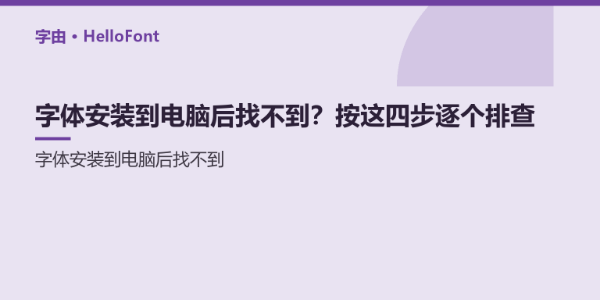
字体安装到电脑后找不到?按这四步逐个排查
字体装完了,字体设置里也能看到,可打开设计软件翻遍字体列表就是没有。或者在自己的电脑上正常,同事打开同一份文件却全部变成宋体。这类问题多数不是字体坏了,而是安装位置、名称显示或软件缓存中的某一环出了偏差。
重装只能解决文件损坏这一类原因,对剩下的情况没有帮助。下面按四个步骤逐个排查,每步都能给出一个明确结论。
一、四步排查的顺序为什么不能颠倒
第一步看安装位置,决定这款字体对谁可见。第二步核对名称,决定你在列表里按什么字去找。第三步刷新宿主软件,决定软件有没有读到新字体。第四步看字体族归属,决定它是不是被折叠进了某个家族的子菜单里。
顺序颠倒会浪费时间:名称没核对清楚就去重启软件,重启完还是找不到;软件没重启就先判定字体有问题,实际只是没刷新。
二、第一步:确认装到了哪个位置
Windows 有两条安装路径,可见范围不同。 双击字体文件后点「安装」,通常装到当前用户目录(%LOCALAPPDATA%\Microsoft\Windows\Fonts),只有当前登录账户能用;右键选「为所有用户安装」,字体进入 C:\Windows\Fonts,本机所有账户可见。
判断方法:打开「设置 - 个人化 - 字体」,这里列出的是当前账户可用的字体。如果在这个账户能看到、换账户后看不到,基本可以确认装成了用户级。另外注意「隐藏」状态,被隐藏的字体不会出现在部分软件的列表里。
macOS 的安装位置分三层。 用户级在 ~/资源库/Fonts,只对当前用户生效;本地级在 /资源库/Fonts,本机所有用户可用;系统级在 /系统/资源库/Fonts,由系统管理。字体册里能看到每款字体所属位置,也能看到它是否处于「停用」状态。
这一步的结论:字体若装在用户级,而你需要在本机所有账户使用,改成「为所有用户安装」或改用其他分发方式。
三、第二步:核对字体名称
中文名与拉丁名不一致。 很多中文字体在系统里同时注册了中文名和拉丁名,软件按不同规则排序时,显示的可能不是你以为的那个名字。已知的例子:思源黑体对应 Source Han Sans,与 Noto Sans CJK 同源;思源宋体对应 Source Han Serif;霞鹜文楷的拉丁名为 LXGW WenKai。按中文搜不到时,换拉丁名再搜一次。
字重名混在家族里。 你装的是「Regular」,但软件族名只显示基础名,字重需要展开家族子菜单才看得到。
核对方法:在系统字体面板里打开这款字体的详情,看它注册的完整名称;再在软件列表里按首字首字母找一遍。两边名称一致却仍找不到,进入第三步。
四、第三步:重启或刷新宿主软件
软件在启动时读取字体列表。 运行中安装的字体,多数软件不会即时识别。Office 系列有时能识别,PS、AI 这类软件通常需要重启。
完全退出再启动,而不是关掉窗口。 关闭文档窗口不结束进程,字体列表不会重新加载。用任务管理器确认进程已结束,再重新打开。
软件与系统各有缓存。 重启软件无效时,尝试重启系统。个别排版软件读取自己目录下的字体,需要把字体文件放进它指定的位置。
这一步的结论:如果重启后字体出现,问题属于缓存;如果始终不出现,进入第四步。
五、第四步:确认字体族归属
字重被折叠在家族子菜单里。 很多软件把同一家族的多个字重收在一个族名下。你看到「思源黑体」,但列表里只有一项,切换字重需要在样式下拉里选 Bold、Medium 等。看起来像少了字体,其实都在。
可变字体的轴被简化。 可变字体用一个文件承载多个字重,部分软件只读出默认实例,需要在字重或轴设置里调整。
检查方法:在字体列表里定位到族名,展开它的样式列表,确认所需字重是否存在。若确实只有一款字重,说明字体文件本身不完整。
排查过程中容易多找一遍的几款字体,附详情入口,便于先看清完整名称与字重结构。
1. 思源黑体
• 风格:开源无衬线体,字重档位多,笔画对比弱、字腔开阔。
• 适配场景:正文与界面文字的通用款。
2. 思源宋体
• 风格:开源衬线体,多档字重,横细竖粗对比克制。
• 适配场景:正式语境正文与标题。
3. 阿里巴巴普惠体2.0
• 风格:中性黑体,笔画端部平直,字面偏大,多字重覆盖。
• 适配场景:电商与运营物料,小字号场景稳定。
4. MiSans
• 风格:现代无衬线体,字面开阔,西文与数字设计完整。
• 适配场景:中英文混排较多的版面与数字表格。
5. 霞鹜文楷
• 风格:基于开源楷体改造,笔画轻盈、结构端正。
• 适配场景:人文类正文与手写感文案。
6. 猫啃珠圆体
• 风格:笔画端部圆润,转角带弧,粗细均匀。
• 适配场景:轻松氛围的物料,餐饮与亲子类设计。
常见问题解答
Q1:字体装好了,Word 里有,PS 里没有,是什么原因?
多数是 PS 没重启。PS 在启动时读取系统字体列表,运行中安装的字体不会即时出现,完全退出进程再打开一般就能看到。若仍没有,检查字体是否被隐藏,或装在了别的账户下。
Q2:macOS 上安装后显示灰色不能用,怎么处理?
灰色通常表示字体处于停用状态或存在重复版本。打开字体册,检查该字体是否被停用;如果同一字体有多个版本,字体册会给出提示,解决重复项后即可正常使用。
Q3:可以不安装就使用字体吗?
可以。客户端激活类工具按需激活字体,不长期写入系统字体目录;网页端还可以用网页字体方式加载。前者适合本地设计,后者适合站点与在线文档。
小结
字体装完找不到,按四步走:先确认装的是用户级还是全局,再核对中文名与拉丁名,然后完全重启宿主软件,再检查字重是否被折叠进字体族。四步过后仍找不到,就要回到文件本身,确认文件是否完整、是否来自可追溯的渠道。
把字体名称、授权类型、来源页记成清单,下次换设备或换软件时能省下同样的时间。